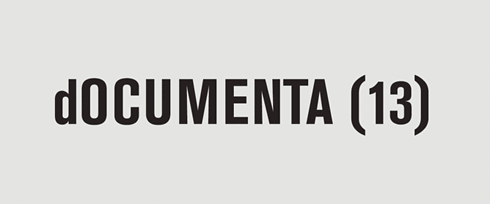
Die Kasseler Documenta kündigt an, dass das Mailänder Designbüro Leftloft in den kommenden Jahren die visuelle Identität der Kunstausstellung entwickeln wird. Seit 1955 hat sich jede Documenta, die im 5-Jahres-Rhythmus stattfindet, durch das Engagement der Organisatoren und der Öffentlichkeit neu definiert. »Die Künstlerische Leiterin der Documenta 13, Carolyn Christov-Bakargiev, hat mit Leftloft einen kongenialen Partner gefunden, um die Anwendung einer Design-Sprache zu entwickeln, die offen, flexibel, spielerisch, einfach und funktional ist und zugleich die Geschichte der Documenta zu würdigen weiß.« heißt es in einer heute veröffentlichten Pressemitteilung.
»Die wahre Identität der Documenta« ergänzt Leftloft »kann als die Summe vieler unterschiedlichen Zeichen und Bedeutungen beschrieben werden, eher als ein Prozess denn eine festgeschriebene Wirklichkeit. Wir glauben, dass dieser Gesamtzusammenhang nicht auf ein spezifisches Grafikdesign reduziert werden sollte.« Daher haben sich die Italiener dazu entschlossen, eine »flexible visuelle Sprache« zu definieren, die dem Wesen der Documenta Rechnung trage und sie nicht festschreibe. Ihr Ziel sei eine durchgängige und effektive »Nicht-Identität« zu erreichen, die nicht auf der Wiederholung eines einzigen grafischen Elements aufbauen werde.
Daher werde die 13te Ausgabe der Documenta kein traditionelles Logo mitführen. Stattdessen gebe es eine Regel für die Schreibweise des Wortes. Es werde am Anfang immer mit kleinen d geschrieben, die folgenden Buchstaben in Versalien, gefolgt von der in Klammern gesetzten Zahl 13. Die Regel soll besagen, »dass die Lehren dieser 13. Documenta (das lateinische ›documentum‹, von dem das Pluralwort ›documenta‹ stammt, bedeutet ›Lehre‹ und gelegentlich bezeichnet es auch eine ›Ermahnung‹) nicht pedantisch sein werden. Wir setzen vielmehr eine lebendige, pluralistische, ideenreiche und stetig zunehmende Entwicklung in Gang. Viele, auch die Öffentlichkeit, werden in den kommenden Jahren in diesen Prozess involviert werden. Der Höhepunkt, im Jahr 2012, stellt nur einen Moment einer viel längeren Reise dar, durch die Klammern um die dreizehn wird das deutlich.«
Die visuelle Sprache der kommenden Documenta werde im Laufe der Zeit durch den Einsatz einer steigenden Anzahl von Schriften unverwechselbar. Jede Schrift sei einem bestimmten Objekttyp zugeordnet, heißt es in der heutigen Verlautbarun. Die Typografie des Namens solle in jeder ihrer Anwendungen variieren, von der Pressemitteilung bis zur Webseite, vom Briefkopf bis zu den Künstler- und Notizbüchern. Es wird also eine Reihe von dOCUMENTA-(13)-Logos zum Einsatz kommen, die sich zwar unterscheiden, doch durch die gleiche Syntax einen gemeinsamen Charakter ergeben.
»Die documenta hat seit ihrem Beginn in den 1950er Jahren in den meisten Fällen ein kleines d anstatt eines großen D’s verwendet«, kommentiert Christov-Bakargiev die Wortmarke der Veranstaltung. »Während dies in ihren Anfängen eine radikale demokratische Geste und eine Entscheidung des Designs war, ist heute die Nicht-Großschreibung von Wörtern ein Beispiel für eine von vielen unbeabsichtigten Gesten der digitalen Welt, die Nachrichten über Netzwerke und rund um den Globus schickt. Die normalen Schreibregeln umzudrehen, indem man das restliche Wort in Großbuchstaben schreibt, erfordert aktives Engagement, Aufmerksamkeit und einen gewissen Mehraufwand an der Tastatur. Leftlofts Entwicklung ist interessant und bringt in ihrer Verbindung zum frühen modernen Grafikdesign des zwanzigsten Jahrhunderts symbolische Bedeutung mit sich.«
»Die visuelle Sprache der kommenden Documenta werde im Laufe der Zeit durch den Einsatz einer steigenden Anzahl von Schriften unverwechselbar.« q. e. d.
Prima konzept. Uneitel. Erst nachgedacht und dann gestaltet.
da wird einem ja ganz künstlerisch um’s herz – bei diesen vielen worten … so mag es der kunstinteressierte. und die projektbeteiligten e-mail-schreiber haben endlich mal ein konzept, dass sich auch von ihnen problemlos umsetzen lässt.
ich bin schon auf die kunst gepannt.
Das wird bestimmt gut aussehen und zu einer passenden Identität der Documenta beitragen. Aber wer sich davon eine durchgängige Nicht-Identität erhofft, der irrt. Denn mitnichten bringt sich die dOCUMENTA dadurch zum Verschwinden.
Bravo!
Ich will hier niemanden beleidigen, aber ich habe hier öfter den Eindruck, dass ihr sogar noch das Bild eines Kothaufens bejubeln würdet, wenn es nur mit genügend blumigen Worten bedacht wäre.
Ein erfrischendes Corporate Design Konzept. Sehr gut!
@ Hans:
Ist ja manchmal auch jubelwürdig:
http://www.c4gallery.com/artist/database/piero-manzoni/piero-manzoni-merda-del-artista-can-shit.jpg
Aber im Ernst: ich halte die dahinter stehende Idee für sehr stark und man wird sehen müssen wie sich das Konzept umsetzt.
@Hans: Wenn er von Piero Manzoni wäre … selbstverständlich!
Sch…, Jens war einige Sekunden schneller ;)
Sorry, aber ich kann damit grade überhaupt nichts anfangen. Begeisterung empfinde ich nicht. Ein wenig pseudo-retro, ein wenig progamiertes Chaos und viele blumige Worte – ich glaube das ist mir zu “künstlerisch”.
Aber vielleicht bin ich auch einfach nicht die Zielgruppe…
Ich finde das Konzept prima. Besonders da ich finde, dass immer mehr ein Logo als Heilsbringer vollkommen überschätzt wird.
Allerdings denke ich, dass bei einem nicht vorhandenen Logo die (typo-)grafischen Ausführungen um so sorgfältiger sein sollten und so stört mich an der oben zu sehenden Ausführung, dass die Versalien gesperrt sind, das kleine “d” aber nicht oder kaum gesperrt zu sein scheint. Blöd.
können wir uns darauf einigen, dass bei (wenn überhaupt) leicht erhöhter laufweite keine rede von »sperren« sein kann und das ein einzelner buchstabe auch nicht »gesperrt« sein kann, weil spationierung stets verhältnis von buchstaben _zueinander_ ist?
björn hat recht; das ›d‹ braucht mehr luft. ebenfalls das versale ›a‹ sowie das ›o‹. dann sitzen die klammern noch beide zu tief. daher wenn schon eine reduzierung bis knapp unter der wahrnehmungsgrenze, dann bitte pingelig-genau spartionieren.
Wow! – Ich bin baff.
Schauen wir auf Sagmeisters CD für die Casa da Música von Porto.
Das ist ein wandelndes Erscheinungsbild. Hier wird gespielt, experimentiert und ein super modulares, weiches Identitätsbild geschaffen welches jeder Veranstlatung die dort stattfindet gerecht werden kann.
Wenn ich nur die Umsetzungen bildlich vergleiche dann vielleicht so:
Ich sehe ein Blatt Papier mit einem Knick auf der einen Seite und ein funktional gefaltenes Stück Origami in absoluter Präzision auf der anderen.
Viel Spaß also mit den halbgaren Eselsohr in Kassel.